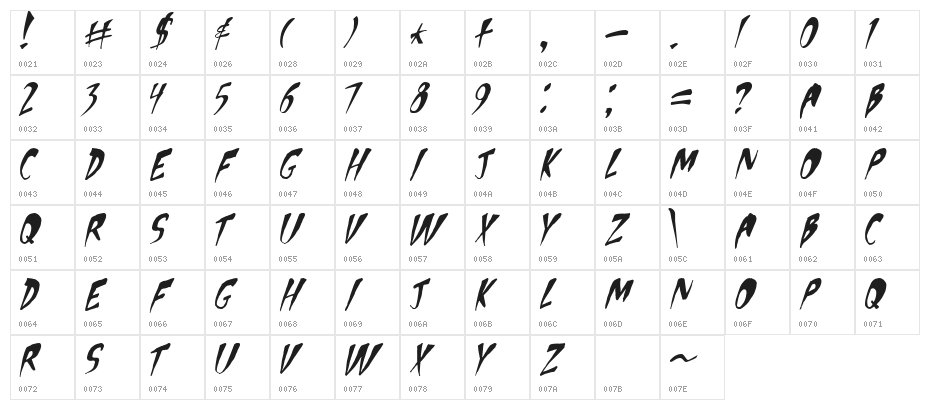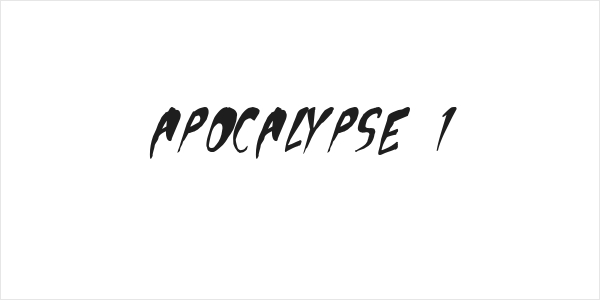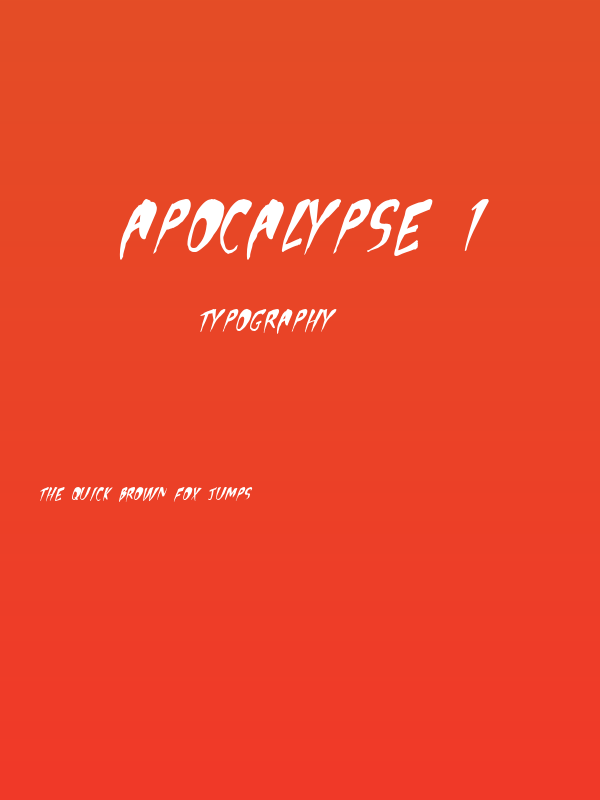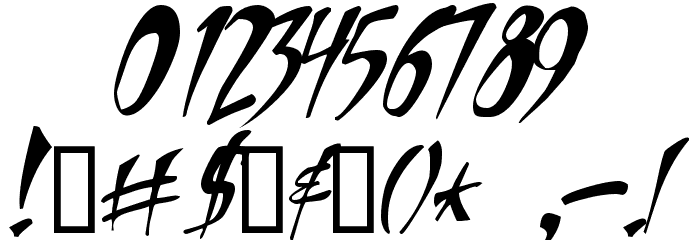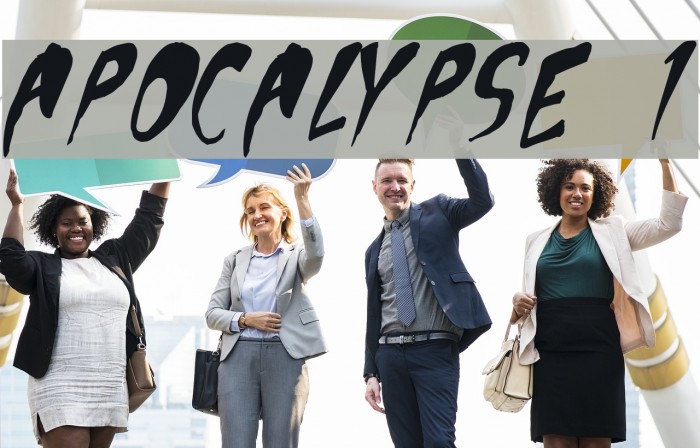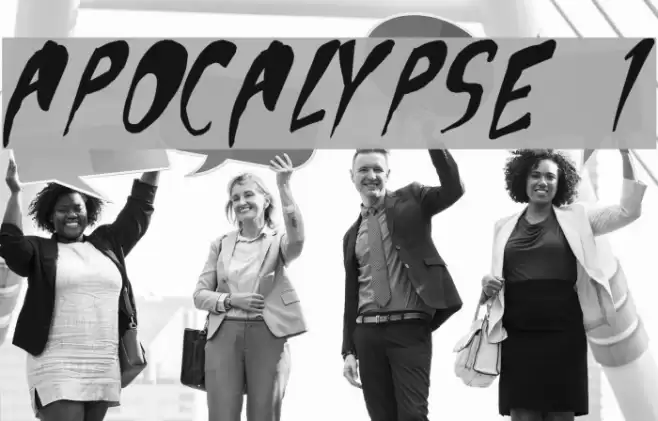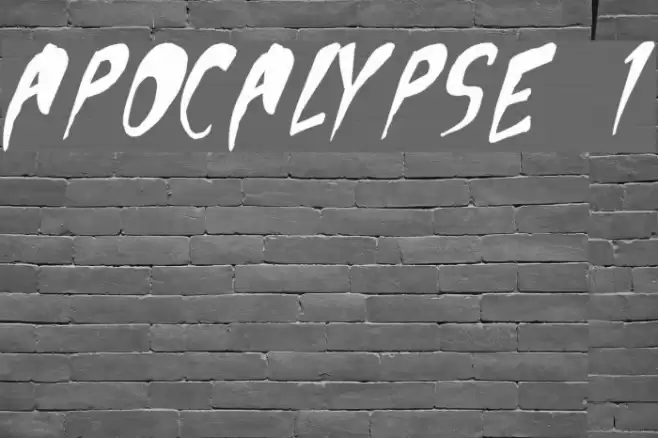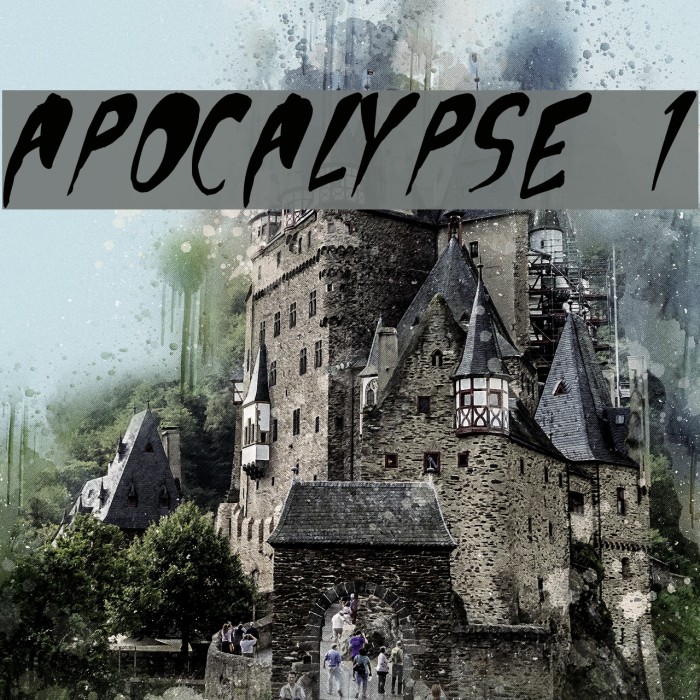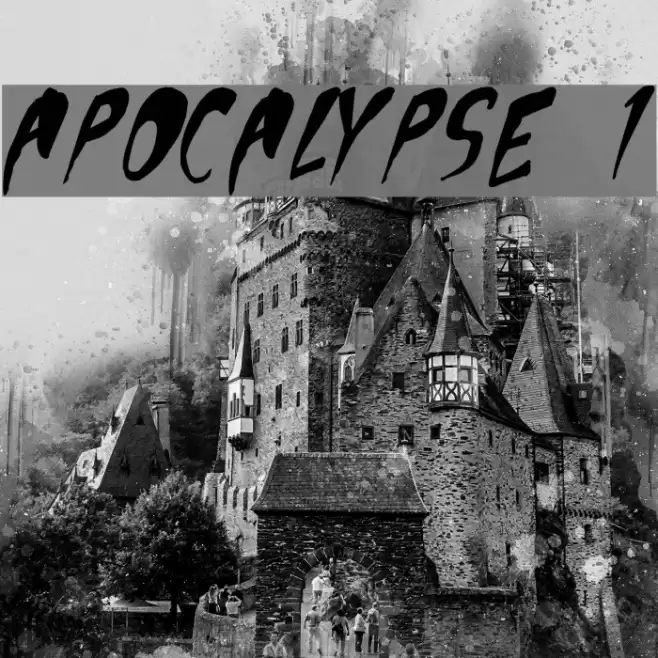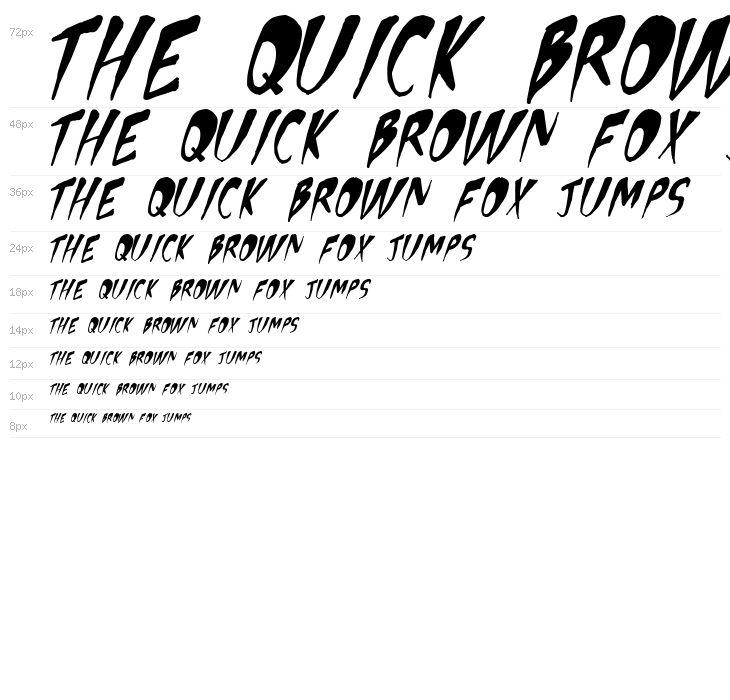
Apocalypse 1 Font
| 全体的なスタイル | Modern, Energetic |
| おすすめプロジェクト | Ideal for movie posters, video game titles, event flyers, and branding that requires a strong, impactful presence. |